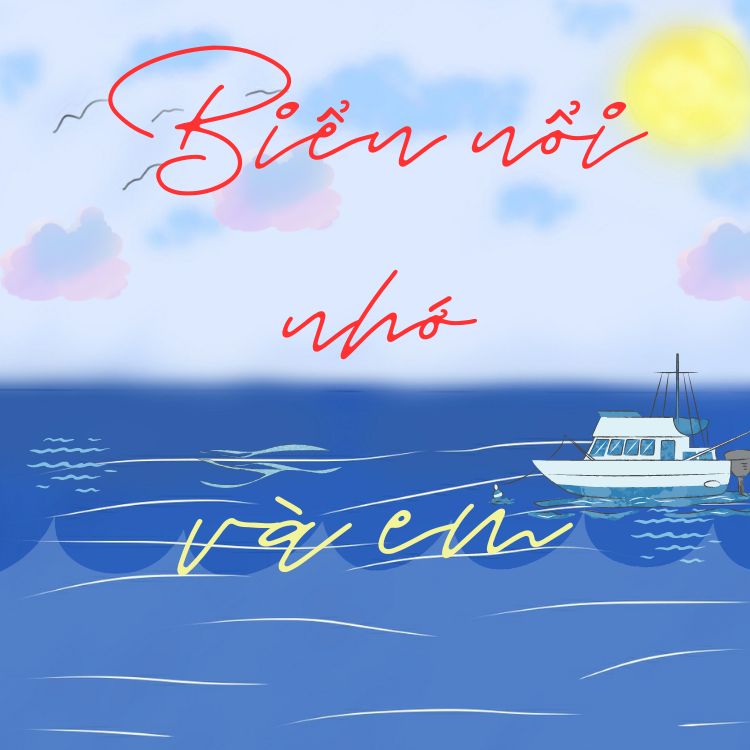
Giới thiệu về Font Việt Hóa MTD Portrait Script Bounce
Trong thế giới đồ họa hiện đại, việc lựa chọn một Font Miễn Phí chất lượng đóng vai trò then chốt giúp sản phẩm trở nên thu hút. Font Việt Hóa MTD Portrait Script Bounce là một trong những bộ phông chữ nghệ thuật được cộng đồng thiết kế ưa chuộng nhất hiện nay. Với phong cách viết tay uyển chuyển và hiệu ứng nhảy bậc (bounce) độc đáo, bộ phông này mang lại cảm giác phóng khoáng nhưng không kém phần tinh tế. Việc sử dụng Font Việt Hóa MTD Portrait Script Bounce giúp các bạn học sinh và giáo viên dễ dàng tạo ra những mẫu thiệp chúc mừng, bìa báo tường hay các bài trình chiếu sinh động, giàu cảm xúc trong môi trường học đường.
Đặc điểm nổi bật của Font Việt Hóa MTD Portrait Script Bounce
Phong cách thiết kế Bounce đầy sức sống
Điểm khác biệt lớn nhất của Font Việt Hóa MTD Portrait Script Bounce chính là cấu trúc đường nét không nằm trên một trục thẳng cố định. Các ký tự dường như đang nhảy múa, tạo nên nhịp điệu vui tươi và hiện đại. Điều này cực kỳ phù hợp cho các dự án thiết kế mang tính cá nhân hóa cao.
Khả năng hiển thị tiếng Việt hoàn hảo
Bộ phông chữ này đã được tối ưu hóa hoàn toàn về dấu tiếng Việt, đảm bảo không xảy ra lỗi hiển thị khi soạn thảo văn bản. Các nét chữ thanh mảnh xen lẫn nét đậm giúp văn bản giữ được sự cân bằng, dễ đọc dù ở kích thước nhỏ hay lớn trên các ấn phẩm in ấn và kỹ thuật số.
Cách ứng dụng và tải Font Việt Hóa MTD Portrait Script Bounce
Để sử dụng hiệu quả, bạn nên kết hợp bộ phông này với các phông chữ không chân (Sans-serif) đơn giản để làm nổi bật tiêu đề chính. Font Việt Hóa MTD Portrait Script Bounce thường được dùng cho logo, tiêu đề trang web hoặc trang trí ảnh kỷ yếu. Hãy nhanh tay sở hữu bộ Font Miễn Phí, Font Việt Hóa, Font Việt Hóa MTD Portrait Script Bounce ngay hôm nay để nâng tầm thẩm mỹ cho mọi tác phẩm sáng tạo của bạn một cách chuyên nghiệp nhất.